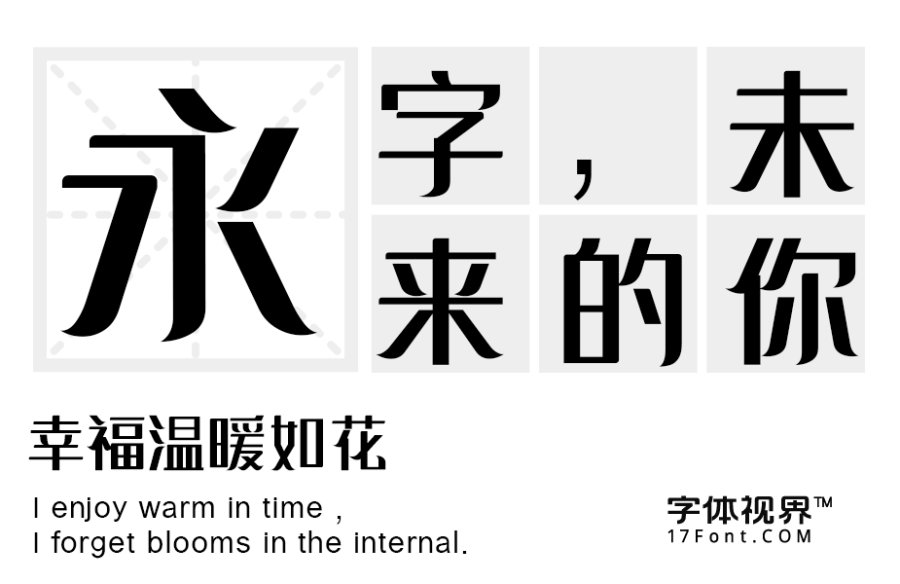
三极能量黑简体发布
字体名称:三极能量黑简体
字体类别: 黑体
三极能量黑简体简介:三极能量黑简体整体用了矩形与弯角两种图形元素来构建,起笔局部做圆弧处理,把笔画概括成飘逸的弧形,并且使左右笔画适当展开尽量对称,最大限度地简化笔画造型。字体结构方正、精致。其字形稳健,个性简静秀美。适用于时尚类品牌的广告和产品包装设计。
三极能量黑简体预览图展示: